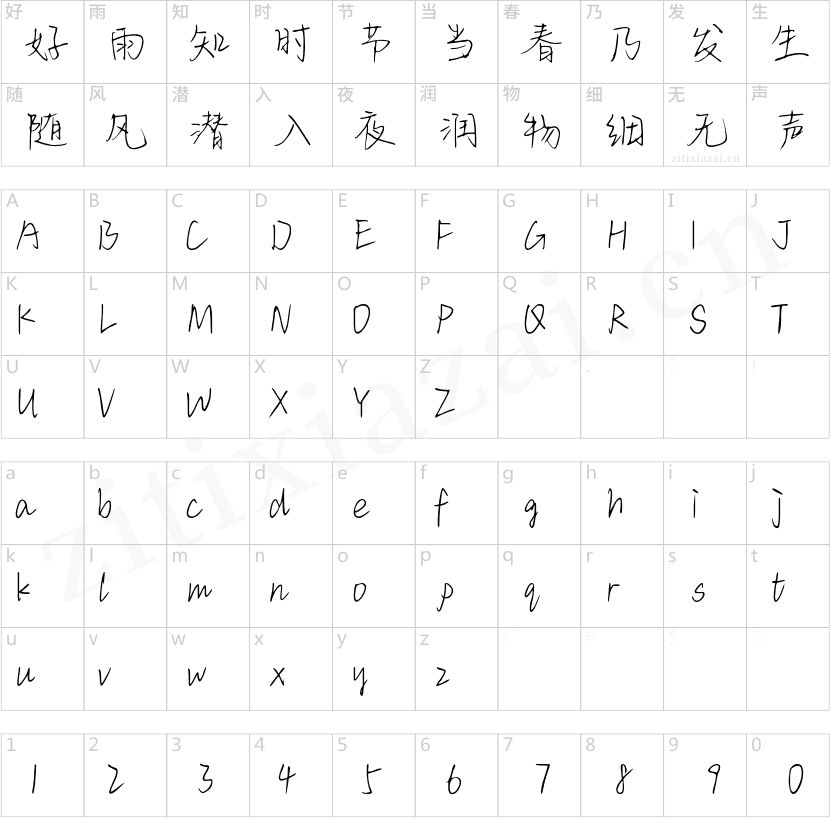
Aa宇宙量贩温柔
Aa宇宙量贩温柔字体
Aa宇宙量贩温柔是一款非常具有艺术性的字体,它的设计灵感来源于对古典艺术的研究,同时又融入了现代字体设计的元素。字形优美,笔画粗细变化自然,给人以大气、典雅的感觉。Aa宇宙量贩温柔是一款既传统又现代的字体,它的设计充满艺术感,美观大方,实用性也非常强。无论是对于设计师还是对于普通读者来说,都是一种非常不错的字体选择。Aa宇宙量贩温柔适合用于具有艺术感的场合,比如海报、宣传单张、书籍封面等。由于其字形流畅且具有动态感,也适合用于大量的文本排版,如报纸、杂志等。